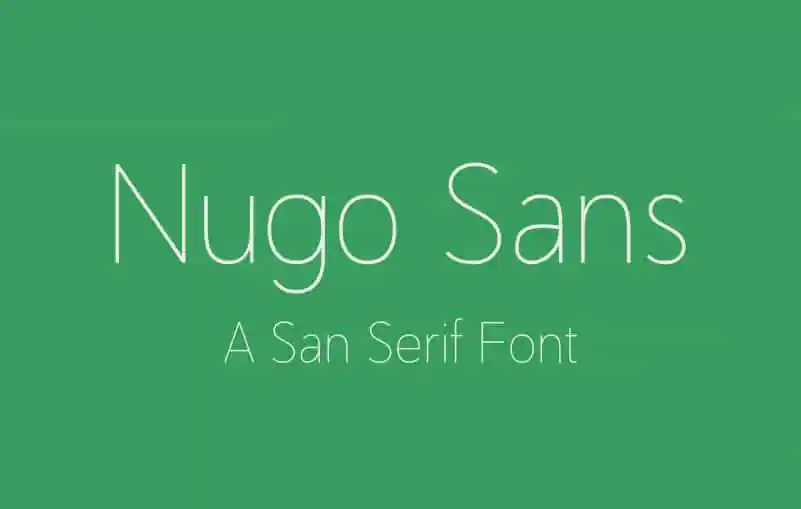
Nugo Sans Free Font é uma moderna fonte de tipo sans-serif com estilo monoline e minimalista, perfeita para encantar seu próximo projeto. Com um aspecto casual e limpo, esta fonte multifuncional se adapta a grande e pequenos tamanhos de texto de maneira ótima. Ideal para aplicar em sites, templates digitais ou qualquer projeto que você esteja desenvolvendo. Suas linhas finas e clean certamente vão manter sua identidade visual em alta estatura. Seja ele um site profissional ou uma simples página do blog, Nugo Sans trará um toque moderno a seu trabalho. Esta fonte gratuita de Hamilton é uma excelente escolha para quem busca beleza contemporânea na web.